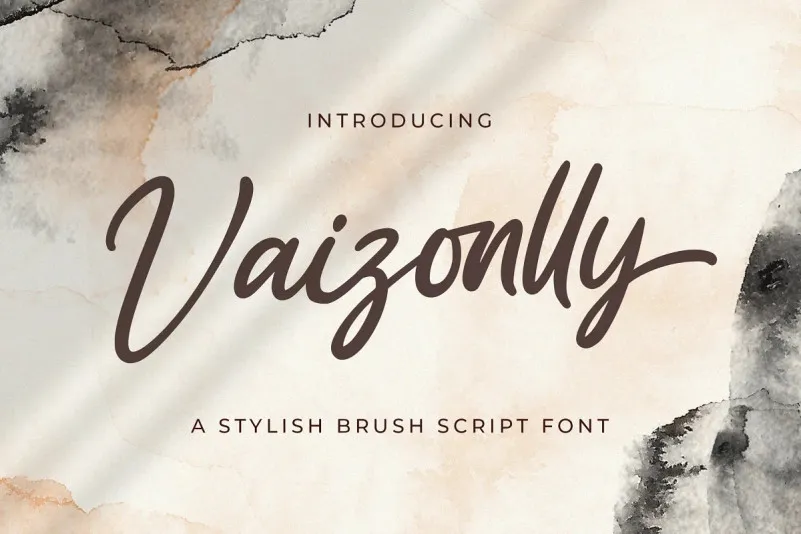
Vaizonlly Script Font – Fonte Grátis
Vaizonlly Script Font
A Vaizonlly Script Font é uma paixão para designers apaixonados por letras manuscritas naturais e estilosas, criada pela StringLabs. Esta elegante fonte é perfeita para adicionar um toque autêntico a qualquer projeto de design. Suas características distintas e inovadoras garantem que sua arte seja única e imortal, mesmo após muitos usos. Quer seja um pequeno detalhe ou o texto principal, ela será uma escolha incrível para tornar suas criações ainda mais especiais. Composta por 149 letras maiúsculas e minúsculas, espaços entre palavras e numeração, a Vaizonlly Script Font é perfeita para aqueles que buscam um toque único e profissional em seus designs de escrita ou gráficos digitais. Aproveite esta fonte para dar vida à sua visão de design, seja ela uma marca de sucesso ou um trabalho fotográfico inovador, a Vaizonlly Script Font estará sempre presente para te ajudar a fazer sua marca brilhar.